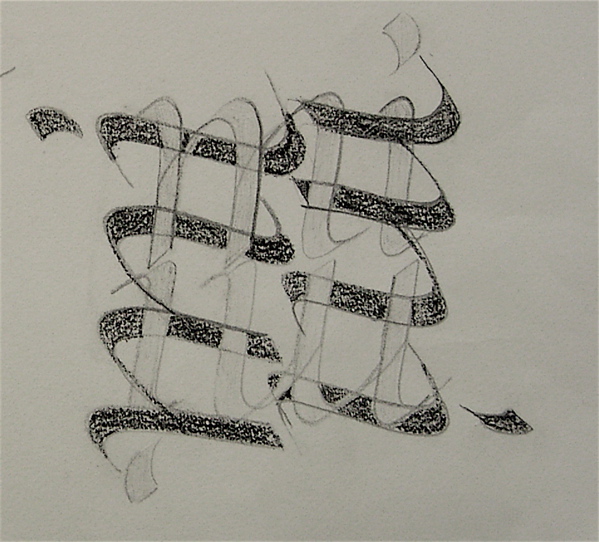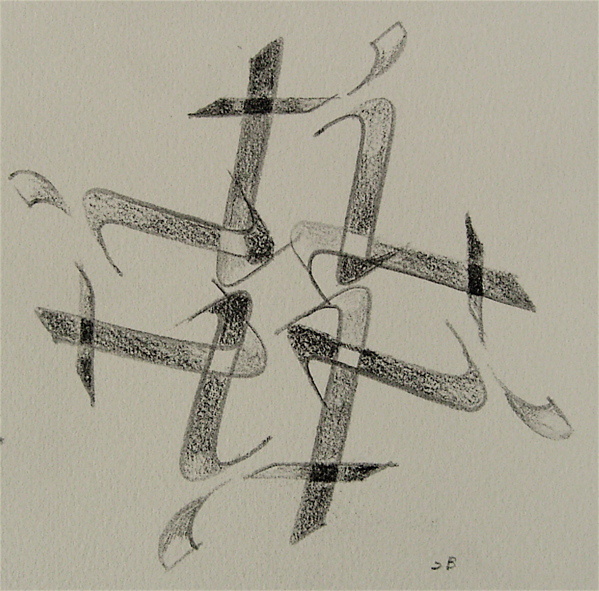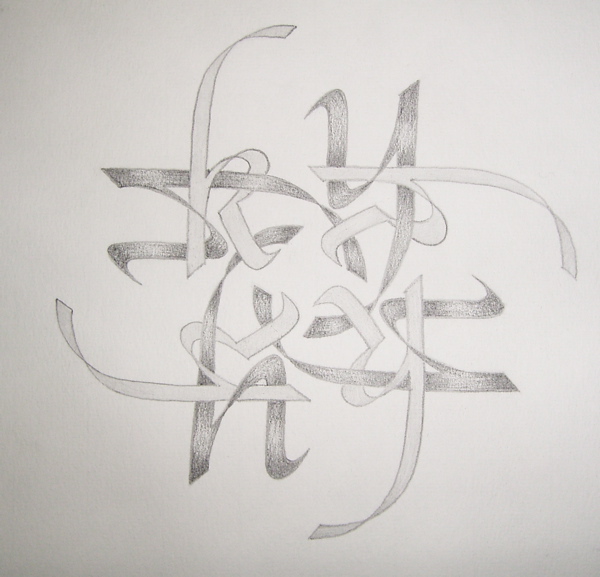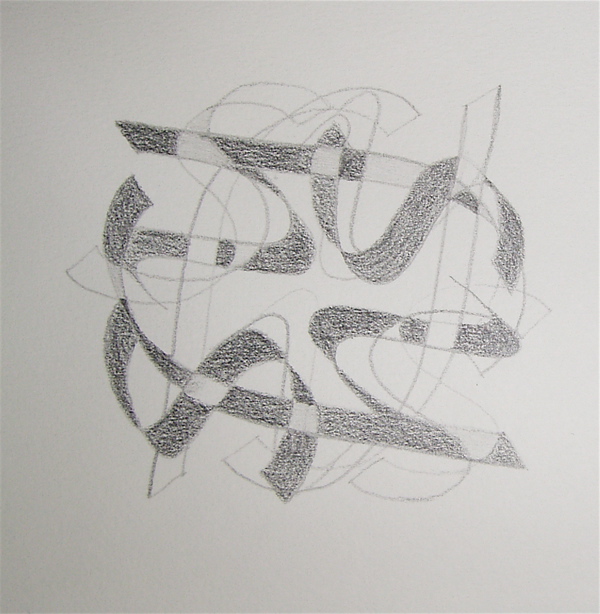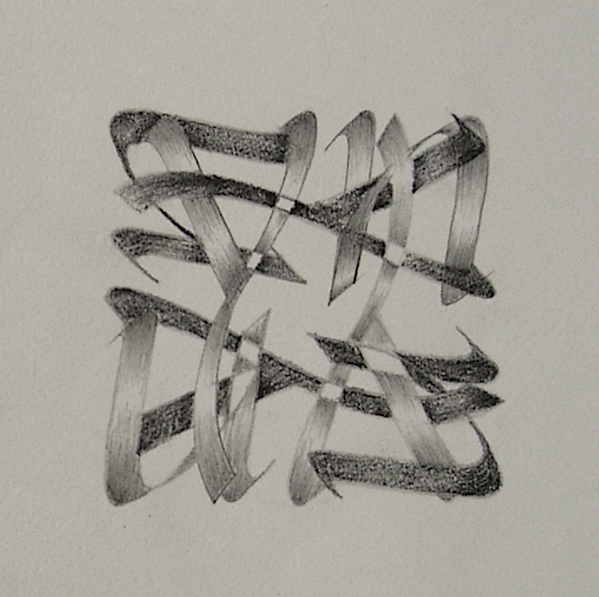
鉛筆でカリグラフィー
これらは先日代々木で行なったクラスの、生徒さんたちの出来上がり作品です。
すべて鉛筆で書いたイニシャルです。
組み合わせによって、ほら、こんなに面白い形になりました。
文字の様にも見えるけど、模様でもあり、どれも本当に良く書けてるでしょう!美しいですね。
文字同士が入り組んで、とても立体的に見えて来るので、不思議。
鉛筆の塗り方でもずいぶん違って見えますね。
薄くても濃くても、それぞれがとても美しい。
さて、こちらは塗ったり消したりしながら、文字を重ねます。
所々陽が当たっているような、格子の陰になっている様な・・・・。不思議な効果です。
同じ言葉ではなく、違うことばが重なっているのもありますよ。
本当はもっともっとたくさんの画像を撮りましたが、すべてをご紹介出来ずに残念です。ここから発展させてどんどん面白い作品に応用していけると良いですよね。
期待しています!
鉛筆でいこう
代々木でのクラスでしたが、今回は鉛筆で楽しむという内容でした。いつもインクやペンや絵の具で書いていますが、たまには乾きものもいいものです。
ダブルペンシルやカーペンターペンシルで文字を書くのは、なかなか気持ちがよいですよ。ペンとは違って摩擦がないから、スルスルっと手が動きます。
コツは下敷きにたくさん紙を置いてクッションをつくること。そうすると、鉛筆が適度に沈み、線がちゃんと出てくれます。けしごむの使い方もポイントですね!書いて消し消し、そして書く。
鉛筆でいこう1
ひとつひとつの文字が大きくなるので、手を一杯動かさないとなりませんが、やわらかな感触なので書きやすいです。
←こちらは、鉛筆で書いた上にペンと顔料系のインクで書きました。
くっきりした黒なので、文字が映えますね。
このクラスは、2時間の中で練習をやってそれから小作品づくりなので、いつも大忙しですが、みなさんの手際の良さとコツの掴み方が上手なのとで、いやいや、いつも感心しきりです。
みんなの作品はまた後日ご紹介しますね。
あ、そう言えば、最後に作った作品は撮影し忘れました!!とっても完成度が高かったので、あ〜、残念!
鉛筆やチャコールを使いこなせたら、世界が広がりますね。
もっと追求してみましょうか!
不思議な温室で身体の記憶を失いながら、そこで出会った男性のもとですの姿を受け入れていく…。小川さんの小説では身体の一つ一つが消えていくお話しが他にもある。そんな奇妙な…と
思う反面、見える物の記憶はあいまいなのかもしれないと思い直す…。BUMP OF CHICKENの Supernovaでも熱が出たりすると自分の身体に気付くということを歌っている…。